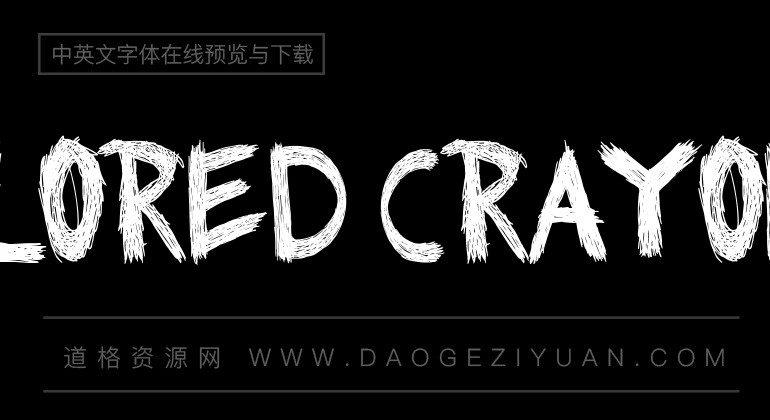
Colored Crayons
Colored Crayons 是一种手写风格的字体,它的设计灵感源于儿童使用的彩色蜡笔。这种字体的字形非常生动有趣,色彩鲜艳明快,可以为各种文本增添浓郁的趣味性和童趣感。 Colored Crayons 字体适用于各种场景,比如广告、海报、儿童书籍、漫画等等。由于其独特的风格和设计,它可以为文本增添独特的个性和特色,同时也可以吸引人们的目光,让文本更具有吸引力和可读性。 总之,Colored Crayons 字体是一种非常有趣和富有创意的字体,可以为文本增添趣味和生动感,是广大设计师和文案编辑者不可多得的选择。
Colored Crayons是一款非常不错的手写艺术字体,具有很好的视觉感,适合于文化类的宣传设计、商业类品牌的广告和产品包装设计以及个性化文字排版等较多场景。
Colored Crayons字符映射图